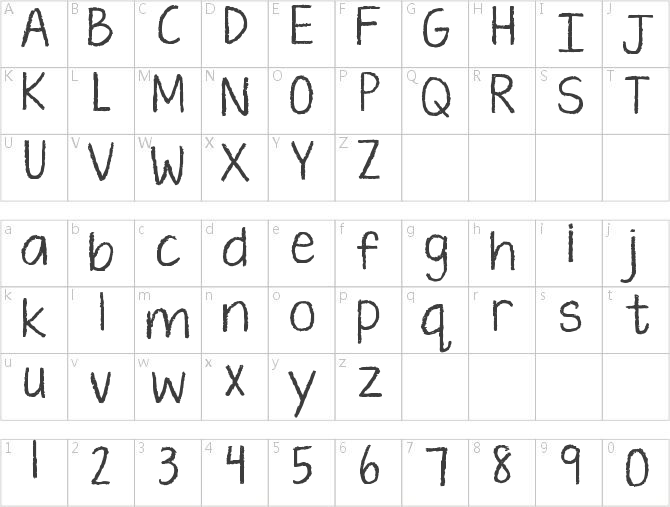
KGTenThousandReasonsAlt
KGTenThousandReasonsAlt介绍
KGTenThousandReasonsAlt字体字库是一款让人赏心悦目、百看不厌的英文字体,适合各类广告和产品包装设计应用,字体大小0.17MB,格式为ttf字体,上传用户是泽泽,作者/版权方为未知